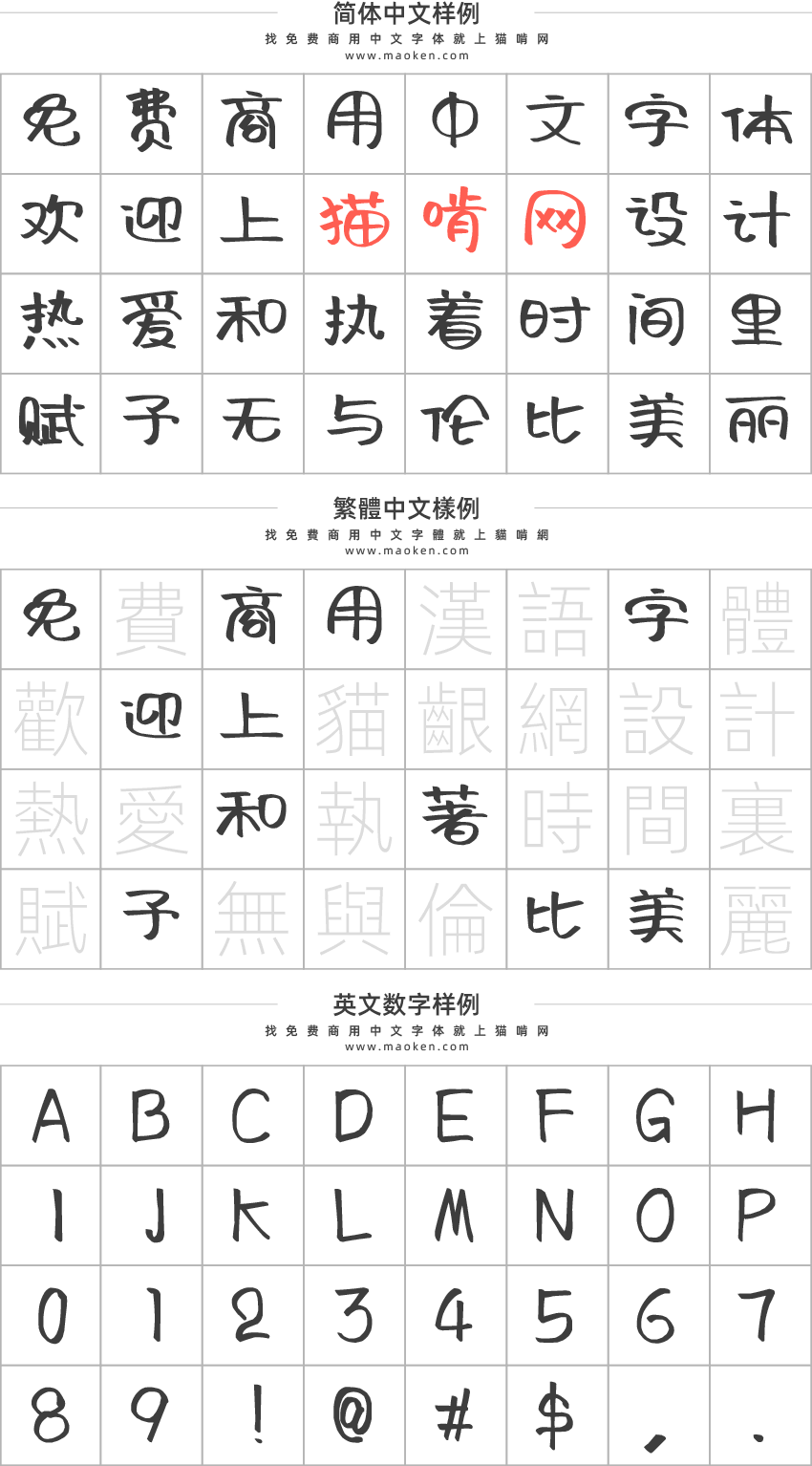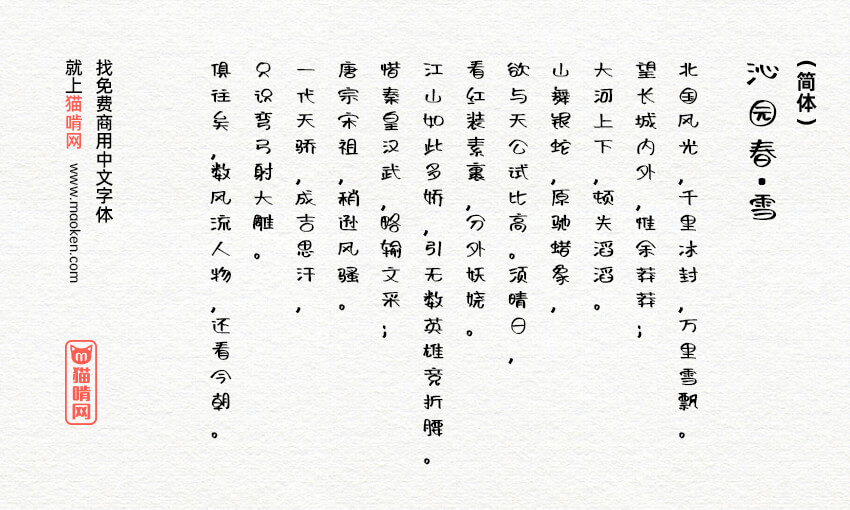
阿朱泡泡体:随意放松充满卡通趣味的手写字形
字体版本:Version 1.9 2019.11.11收录汉字:简体★★★★★ / 繁体★
阿朱泡泡体发布于2019年的光棍节,这是一款字体书写笔画随意放松,富于变化,充满卡通趣味极富装饰色彩,特别是口型偏旁由“泡泡”组成,使字体充满青春活力风格鲜明,特点突出,能够适用于艺术设计、包装印刷、签名设计、图形设计等领域,有喜欢的朋友可免费下载收藏。
字数:本字体基于中华人民共和国GB2312-80字符集标准,共收容汉字6763个汉字和数百个符号。